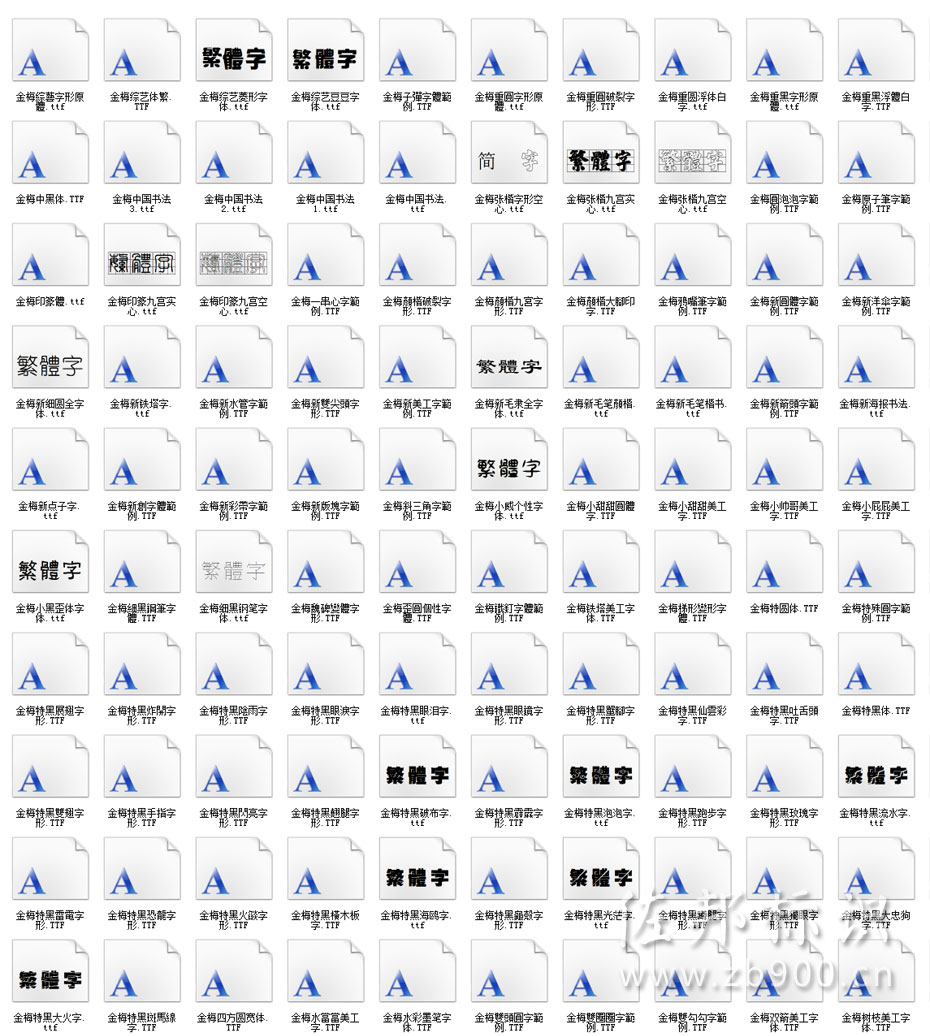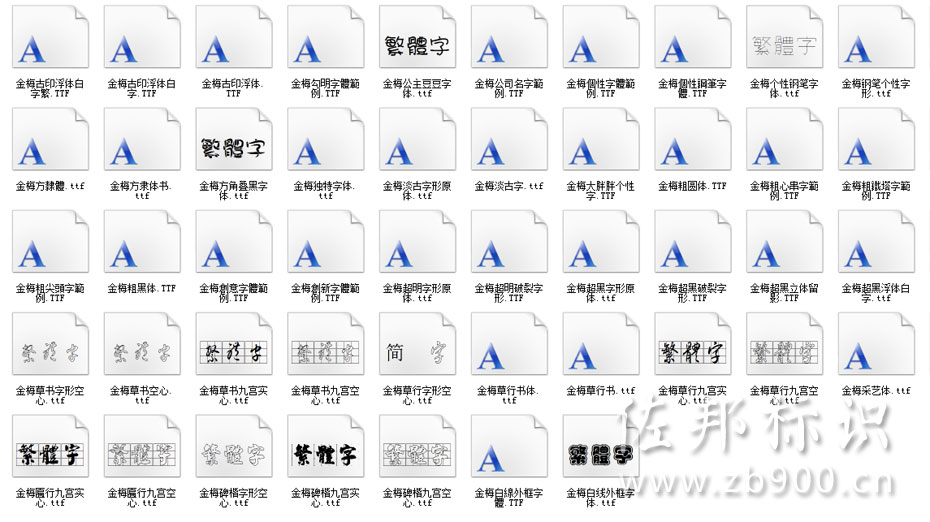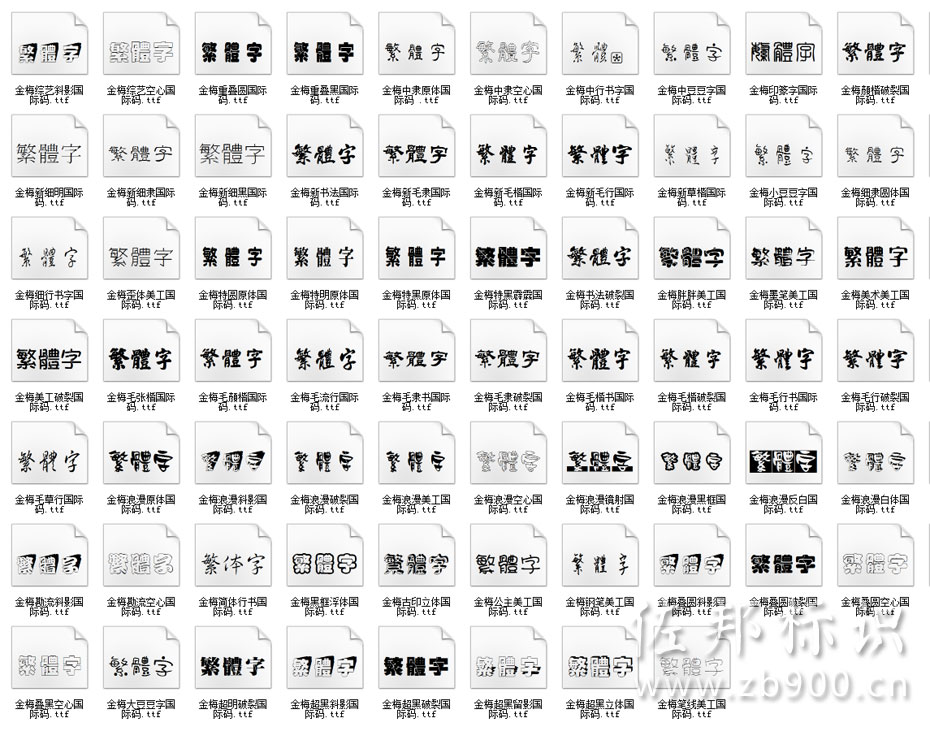
金梅字库系列是一款仿毛笔书法的中文字体,同时也是一款繁体字库,在使用时候要注意,这款字体需要使用繁体输入法(推荐使用陈桥五笔输入,不会五笔的也可以使用拼音输入)。
“金梅字体下载”由【佐邦标识】小编整理而成,为目前较为全面的金梅字库,包含:272款BIG5码和74款国际码,金梅字体,广泛应用于书法设计、名片设计、平面广告等行业;不过由于字库较老,很多文字不能正确显示,如果出现这种情况,可以选择拼接法使用。就是打两个能正确显示的部分,再行拼结
金梅粗麥克字範例  金梅浪漫飘酒字体  金梅毛流行体  金梅特黑裂开字 金梅新啞鈴字範例
金梅粗鐵塔字範例 金梅浪漫破裂字形 金梅毛書法九宫字 金梅特黑流水字 金梅新洋伞字範例
金梅粗心串字範例 金梅浪漫閃電字形 金梅毛顏楷  金梅特黑玫瑰字形 金梅新圓體字範例
金梅粗圆体  金梅浪漫體  金梅毛顏楷体  金梅特黑跑步字形 金梅鴉嘴筆字範例
金梅大胖胖个性字  金梅浪漫娃娃字体  金梅毛张楷体  金梅特黑泡泡字 金梅顏楷大腳昨字
金梅淡古字 金梅浪漫小叠字体  金梅毛張楷  金梅特黑孬霖字形 金梅顏楷九宮字形
金梅淡古字形原体  金梅浪漫小胖字体  金梅毛正楷九宫字 金梅特黑破布字 金梅顏楷破裂字形
金梅独特字体  金梅浪漫优雅字体  金梅美工爱心字形 金梅特黑翹腿字形 金梅一串心字範例
金梅方角叠黑字体  金梅浪漫中圆字体  金梅美工变体字形 金梅特點亮字形 金梅印篆九宫空心
金梅方隶体书  金梅兩頭尖字範例  金梅美工大头字体 金梅特黑手指字形 金梅印篆九宫实心
金梅方隸體  金梅流行書 金梅美工刀字範例 金梅特黑雙翅字形 金梅印篆體
金梅飛彈字鱧範例  金梅落葉美工字鱧 金梅美工叠黑字体  金梅特黑水花字形 金梅印篆字形空心
金梅钢笔个性字形 金梅麦克字体  金梅美工豆豆字体 金梅特黑体  金梅原子筆字範例
金梅个性钢笔字体  金梅麥克字鱧範例 金梅美工风味字体  金梅特黑吐舌頭字  金梅囿泡泡字範例
金梅個性鋼筆字體 金梅毛碑楷  金梅美工钢笔细字  金梅特黑仙雲彩字  金梅张楷九宫空心
金梅個性字體範例 金梅毛碑楷体  金梅美工古印字体  金梅特黑蟹腳字形 金梅张楷九宫实心
金梅公司名字範例 金梅毛笔匾行书 金梅美工广告字体 金梅特黑眼镜字形 金梅张楷字形空心
金梅公主豆豆字体  金梅毛笔草楷  金梅美工空心字形 金梅特黑眼泪字 金梅中国书法
金梅勾明字鳢範例 金梅毛笔行书  金梅美工破裂字形 金梅特黑眼淚字形 金梅中国书法1
金梅古印浮体  金梅毛笔隶属 金梅美工甜甜字形 金梅特黑陰雨字形 金梅中国书法2
金梅古印浮体白字 金梅毛笔张楷书  金梅美I鐵縋字形 金梅特黑炸開字形 金梅中国书法3
金梅古印浮体白字繁  金梅毛匾行  金梅美I香腸字形 金梅特黑展翅字形TIP 金梅中黑体
金梅海报标题字体  金梅毛草行国际码 金梅美I新创字体  金梅特明体  金梅重黑浮体白字
金梅海报大豆豆字 金梅毛草行体  金梅美I虚线字体  金梅特殊圆字範例  金梅重黑浮體白字
金梅海报叠圆字体  金梅毛草书 金梅美工忠狗字形 金梅特圆体  金梅重黑字形原體
金梅海报书法字形 金梅毛草书国际码 金梅美術工藝字體  金梅梯形變形字體  金梅重圆浮体白字
金梅综艺菱形字体  金梅综艺豆豆字体  金梅子彈字體範例 金梅重圆字形原體  金梅重圆破裂字形
金梅综艺体繁 金梅綜婪字形原體
字体预览
金毛字体预览
金梅74款国际码字体清单
金梅综艺斜影国际码  金梅综艺空心国际码 金梅重叠圆国际码 金梅重叠黑国际码 金梅中隶原体国际码
金梅中隶空心国际码  金梅中行书字国际码 金梅中豆豆字国际码 金梅印篆字国际码 金梅顏楷破裂国际码
金梅新顏楷国际码 金梅新细明国际码 金梅新细隶国际码  金梅新细黑国际码 金梅新书法国际码
金梅新毛隶国际码 金梅新毛楷国际码 金梅新毛行国际码  金梅新草楷国际码 金梅小豆豆字国际码
金梅细隶圆体国际码  金梅细黑圆体国际码 金梅细行书字国际码 金梅歪体美工国际码  金梅特圆原体国际码
金梅特明原体国际码 金梅特黑霹霖国际码 金梅书法破裂国际码 金梅胖胖美工国际码
金梅墨笔美工国际码  金梅美术美工国际码  金梅美眉美1工国际码  金梅美工破裂国际码 金梅毛张楷国际码
金梅毛顏楷国际码 金梅毛流行国际码 金梅毛隶书国际码 金梅毛隶破裂国际码 金梅毛楷书国际码
金梅毛楷破裂国际码 金梅毛行书国际码 金梅毛行破裂国际码 金梅毛草书国际码 金梅毛草行国际码
金梅浪漫原体国际码  金梅浪漫斜影国际码 金梅浪漫破裂国际码 金梅浪漫美工国际码  金梅浪漫空心国际码
金梅浪漫镜射国际码  金梅浪漫黑框国际码 金梅浪漫反白国际码 金梅浪漫白体国际码 金梅宽钢笔字国际码
金梅勘流斜影国际码  金梅勘流空心国际码 金梅简体行书国际码 金梅黑框浮体国际码 金梅古印立体国际码
金梅公主美工国际码  金梅钢笔美工国际码  金梅叠圆斜影国际码 金梅叠圆破裂国际码 金梅叠圆空心国际码
金梅叠黑斜影国际码  金梅叠黑空心国际码 金梅大豆豆字国际码 金梅超明破裂国际码 金梅超黑斜影国际码
金梅超黑破裂国际码  金梅超黑留影国际码 金梅超黑立体国际码 金梅笔线美工国际码